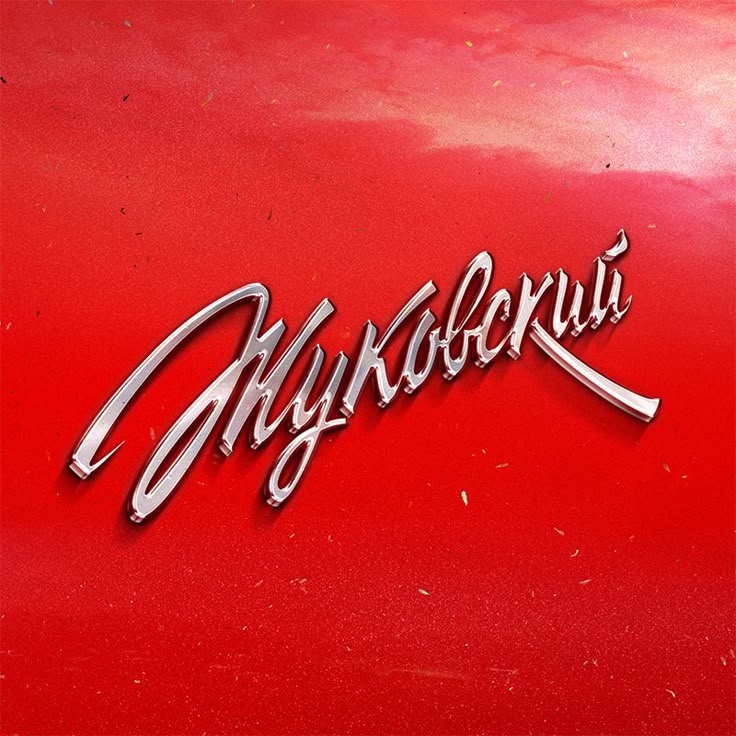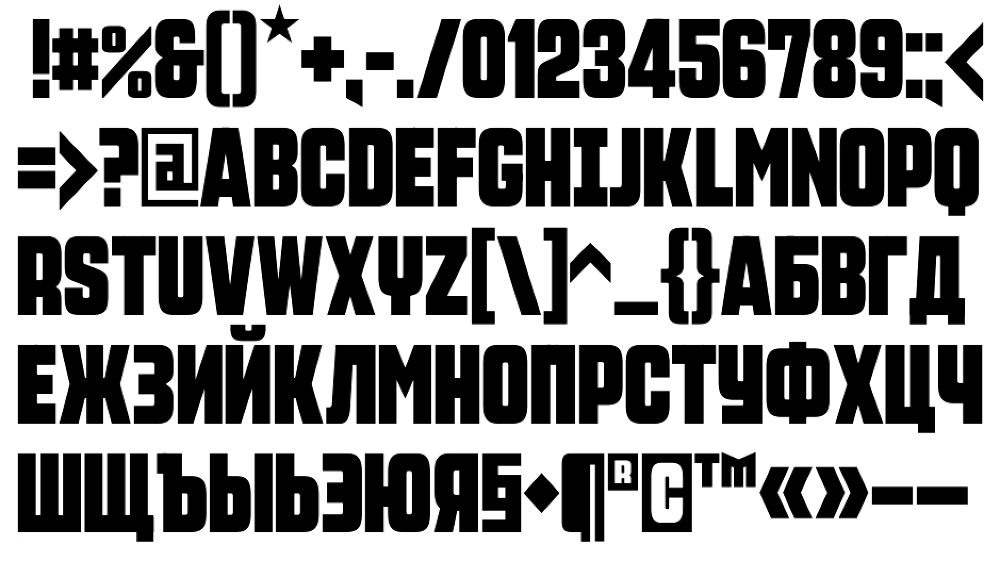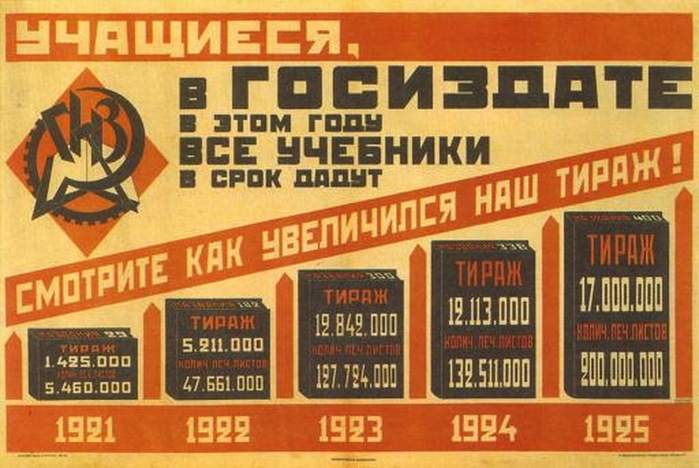
Советские плакатные шрифты. Мир «ВКонтакте» Что такое советский леттеринг и как он появился
Как только я начал серьезно заниматься дизайном, сразу стал обращать больше внимания и на шрифты: от современной типографики до вязи, от экспрессивной каллиграфии до швейцарской школы. Тогда я и познакомился с советским леттерингом, и тут же захотелось создать паблик с уникальной темой и контентом. Так родился «Советский леттеринг» . Образцы советской шрифтовой школы в интернете можно было собирать только по крупицам: рыться в подборках кинотитров, просматривать старые фотографии или изучать диафильмы. А это сообщество было создано, чтобы собрать весь пласт культуры в одном месте.
Для себя я выделил 3 основных причины появления советской шрифтовой культуры.
Революция и художники-авангардисты
Дух нового времени требовал новой графики. Тени, блики, рюшечки и витиеватые шрифты были выкинуты в корзину за ненадобностью, а им на смену пришли четкие формы и минимум цветов.
Железный занавес
Советские дизайнеры имели очень ограниченный доступ к информации извне и не могли в полной мере вдохновляться работами иностранных коллег. Они варились в собственном соку. Казалось бы, создались все условия для угасания и деградации шрифтовой культуры. Но здесь нам очень повезло с художниками-оформителями, которые при таком положении вещей не стояли на месте, а, наоборот, темпами советской промышленности развивали новую шрифтовую культуру.
Стандарт 1337 «Шрифты гартовые»
В 1930 году в СССР произошло важное для всей полиграфической промышленности событие. В феврале Всесоюзным комитетом по стандартизации был принят обязательный Общесоюзный стандарт 1337 «Шрифты гартовые». Этот небольшой двухстраничный документ ограничил советских дизайнеров определенным набором шрифтов (всего 20 гарнитур и 31 начертание). Сюда вошли гарнитуры «Обыкновенная», «Учебная», «Латинская» и т.д. Все шрифты, не вошедшие в список, должны были быть отправлены на переплавку.
Шрифт как неотъемлемая часть культуры
Невозможно себе представить советскую улицу без неоновой вывески «Универмаг», советское кино без динамичных, размашистых титров, советскую книгу без красивой минималистичной обложки или советский плакат без фирменной узнаваемой графики. Шрифт был неразрывно связан с культурой и историей.
В паблике уже несколько тысяч человек, и многие из них предлагают в новости свои фотографии. Кому-то понравилась старая вывеска в деревне у бабушки, кто-то взял в библиотеке старую книгу и восхитился обложкой, а кто-то фотографирует старый холодильник дома у родителей.
Недавно одна из подписчиц поделилась с сообществом подборкой прекрасных афиш, которые она нашла в архиве свердловского театра. А ведь они могли бы и никогда больше не увидеть свет.
Примечательна история вывески универмага в Перми. Шикарные размашистые буквы «Пермь» красовались на крыше магазина со дня его открытия 29 декабря 1965 года. Но по мнению нынешних владельцев здания, вывеска уже не вписывалась в окружающий пейзаж и выглядела как пережиток прошлого, особенно по соседству с логотипом «Макдоналдса». Ее заменили на простую и довольно безликую светодиодную надпись «ЦУМ», набранную шрифтом Magistral.
И хотя многие старые вывески сейчас находятся в плачевном состоянии, многие владельцы понимают их прелесть и ценность. Например, прогуливаясь по Петербургу, можно заметить множество ухоженных старых неоновых вывесок, которые висят там уже лет 50, а выглядят как новые.
Значит, культура еще жива, а это не может не радовать.
Надеюсь, ценителей советской шрифтовой культуры станет больше и люди будут чаще обращать внимание на старые вывески и книги. А сейчас советую взять в руки фотоаппарат и пройтись по своему городу в поисках скрытых шрифтовых сокровищ.
В своём знаменитом очерке «Украшение и преступление» 1908-го года модный тогда архитектор Адольф Лоос писал: «Развитие культуры влечёт за собой вытеснение орнаментальности из оформления повседневных вещей». Этим утверждением он исключал множество вычурных декоративных шрифтов, разработанных на протяжении прошлых столетий, из применения в дизайне высокого класса. А теперь быстренько вернёмся в наши дни: в Web 3.0 полно почти ровных шрифтов без засечек и классических прямых шрифтов, поэтому дизайнерам так не хватает излишеств книгопечатников былых времён.
Возьмите на вооружение мощную выразительность антикварных шрифтов и придайте вашей графике очарование старины, очень модное сейчас и в печатных, и в онлайн-проектах.
От ковбойского и викторианского стилей до авангарда и каллиграфии — выбор весьма широк. Шрифты сгруппированы произвольно, современные интерпретации могут соседствовать с (почти) подлинными прототипами. Все они доступны бесплатно для применения в частных проектах, только, пожалуйста, не забывайте внимательно читать лицензионные соглашения.
Имитации оттисков с деревянных досок и плакатные шрифты
Этот напоминающий дешёвые оттиски с деревянных досок шрифт не лишён своего шарма: от него веет блёклыми афишами захудалого театрика. Вид в равной степени мрачный и вызывающий, подходит для графики на сюжеты от неформальных до пугающих.